Netflix出品,汇集世界六大顶级设计师
2017年,一部关于文化创意时尚工业领域艺术纪录片《抽象:设计的艺术》,豆瓣评分9.4,国外烂番茄网评分高达92%的神级纪录片。
时隔2年,第二季火爆回归~
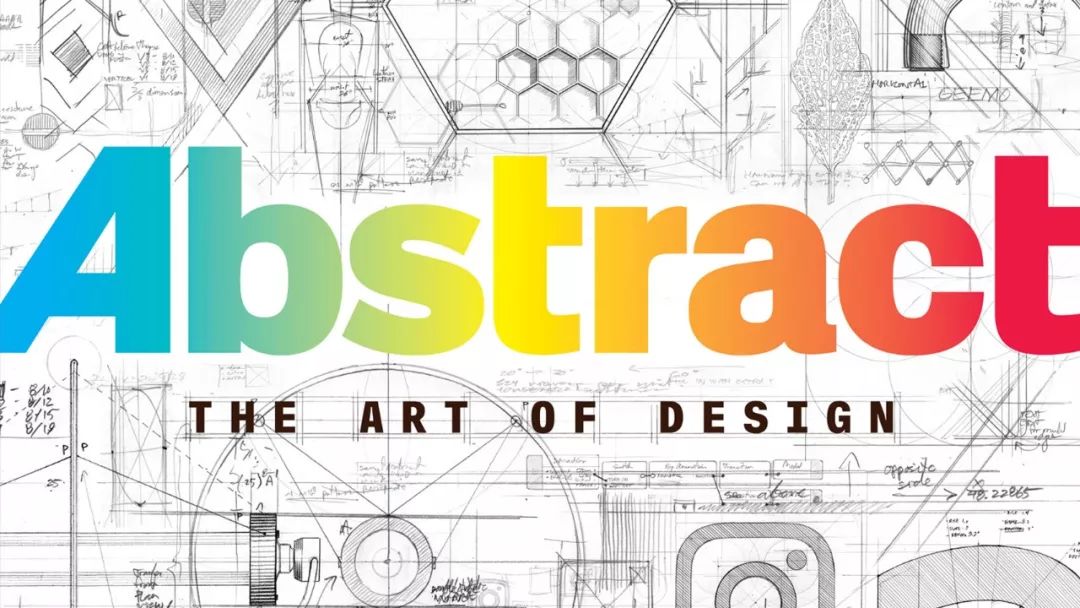
不愧是Netflix力作,一开播就引起巨大反响,目前豆瓣也已达到9.1分,预估有望超过第一季。
这一季由奥斯卡最佳纪录长片导演伊丽莎白·柴·瓦沙瑞莉执导,共探访了6位设计师。他们包括
玩材料的麻省理工美女博士
instagram前设计主管
漫威《黑豹》的服装设计师
脑洞大开的玩具设计师
《时尚芭莎》、《纽约时报》等原版杂志字体开创者
还有打造沉浸式体验鼻祖
与第一季不同的是,内容上更多的是介绍他们对设计的思考理解,从而让我们更好地理解什么是设计,以及创新设计真正的意义和价值。
「麻省理工的“疯子教授”」
Neri Oxman / 生物建筑
皮特的“绯闻女友”让很多人注意到了这位MIT的美女博士,但认识她的人,早已知道Neri Oxman 这个名字已经成为传奇。
建筑师、设计师、发明者三个身份集于一身,是一位名副其实的女学霸。作为世界建筑界的五位顶尖女设计师之一,连纽约现代博物馆、巴黎蓬皮杜艺术中心等全球顶级博物馆收藏着她的作品。
▲死亡面具
▲贵妃椅:采用44种不同的复合材料,由木质外壳和3D打印的细胞形状的表皮结合而成的躺椅
她创造并实践着一个新的词语“材料生态学(Material Ecology)”。试图通过“大自然启发设计”原则来增强建筑、自然和生物环境之间的关系。
希望在未来有更加新颖的技术发明,能广泛的应用于建筑、服装、产品等设计行业。
▲6500只蚕制造的蚕丝亭
融科技与设计为一体,理念前卫,造型独特是她作品的一惯风格。有精密生长的生物感,又有新材料带来的新鲜感,让人感觉空灵而神秘。
▲Rottlace
▲Aguahoja 项目
第一眼看到奈利的作品是惊呼美,当了解其中大致的科学原理,就会更崇拜她的创造力。因为这些非凡作品的背后,讨论的是改变人物未来的伟大决心和持之以恒的实践。
▲3D打印的生物可穿戴设备,其特点是可作为微生物的栖息地,在恶劣环境下能产生糖或生物燃料,维持使用者的生存
▲描绘的一种设计世界的新模式: 有机体世界
▲实现世界上第一个玻璃的3D打印
「Instagram 前设计负责人」
Ian Spalter / 产品设计
顶着一个爆炸头的潮酷伊恩,曾在Instagram、YouTube、Foursquare、R / GA 、Nike多家公司任职。在他看来,数字产品设计,不仅仅是用户体验设计,也关于整体产品策略,需要研究和考虑用户的使用需求。
2016年,Ins从相机logo换成现在的彩虹logo时,引起全球一片哗然,各种新闻媒体、社交媒体毫不留情的批评声此起彼伏。那是伊恩加入Instagram的第一个杰作。
▲目前拥有超10亿用户的社交应用软件Instagram
新logo采用扁平化、渐变色、非衬线体、动态化,外观更简洁直观,已经成为当下最流行的图标设计趋势。
片中伊恩从人机交互界面的历史谈起,界面作为人与机器之间交流的平台,在生活中如何被开发。
用户体验设计(UX)和交互界面设计(UI)的如何更加操作简化,方便用户的理解,通过更直观的感受,不需要经过学习直接就能使用。
设计需要针对人性以及市场深度需求,给出具体的解决方案才行,而不仅仅是关注“好不好看”。
「沉浸式体验鼻祖」
Olafur Eliasson / 艺术设计
奥拉维尔以雕塑和大型装置艺术而闻名,是目前最受青睐的十大国际艺术家之一,可以说世间万物都能被他玩转到一起,大到自然气象,小到各类金属。
自然、光、色彩和几何构成是他作品中不断出现的主题。使用人造装置来重现自然景观,把美感表达到极致,所以说他是沉浸式体验鼻祖。
他在巴黎的凡尔赛宫“挂瀑布”,在伦敦泰特博物馆“种太阳”,吸引数百万观众前去观赏奇观。
▲《天气项目》
▲小太阳计划:帮助全球11亿仍生活在无电网覆盖地区的人们,能够看到光亮
利用错觉触动观众的官能感知,参与者在其中失去空间感和视角,完全被强光所包含,被色彩、被几何的魅力所吸引。
他说得最多的话是把想法变成行动,这也是他的设计理念和工作模式,让观众去亲身感受、亲自参与,而不仅仅把作品停留在简单的看与思考的层面。
▲2007年伦敦蛇形画廊馆
▲丹麦城堡办公厅
「儿童玩具设计得最好的厨师」
Cas Holman / 玩具设计
卡斯是玩具设计界的多领域大神,但他是从厨师跳入家具制造,然后涉足生物多样性研究,参与幼儿教育,又攻读了3D设计,所以说不想做玩具的设计师不是个好厨子。
她第一个成功的玩具设计是Geemo,一个大型建筑套件玩具,于2006年在现代艺术博物馆的设计商店推出,这正式开启了卡斯的玩具职业生涯。
她设计的玩具通常由多种不同形状的建造单元组成,可以在户外或室内使用。孩子们可以自由拼接,组装出自己设计的物件和装置,为个人的想象留下更多空间,开发了孩子们的创造力。
她质疑传统玩具的形式,那种被符号化的风格在她看来并不是真正为孩子设计的产品。作为一名设计师,她要做能让儿童自由想象、探索想法和发明新事物的玩具。
「漫威电影《黑豹》的服装设计师」
Ruth Carter / 服装设计
她是一名美国电影服装设计师。2019年,漫威大片《黑豹》斩获奥斯卡最佳服装设计奖,露丝也成为首位获得奥斯卡服装设计奖的非洲裔美国妇女。
▲《黑豹》剧中服饰
在获奖之前,露丝几乎名不见经传,尽管她已经为40多部电影或电视剧设计服饰,也曾因为两部电影获得过提名。
对她而言,她觉得缝衣服这件事,就像是在讲故事。她给电影和戏剧的演员们设计服装,也是在为作品构建一个鲜活真实的世界。
露丝说她很喜欢观察街上的路人,人们用衣着记录生活,体现自身的价值观,想象他们经历过的故事。
抓住时代的精髓,结合不同文化场景的缩影,打造出适合他们的视觉身份。
「《滚石》《时尚芭莎》杂志字体开创者」
Jonathan Hoefler /  字体设计
生活在纽约的字体设计师乔纳森·霍夫勒,向观众们讲述了字体设计背后的故事。作为当今美国最知名的字体设计师之一。
曾为各个时期最有影响力的杂志设计过封面字体——《滚石》《体育画报》《时尚芭莎》《时尚先生》等,用于珠宝品牌 Tiffany & Co.品牌形象更新。
圈外人可能不熟悉他本人,但是他创建的Macintosh计算机字体和Gotham字体,随处可见,从苹果字体到奥巴马2018年总统大选海报设计。
▲霍夫勒创建的Gotham字体
▲奥巴马总统竞选海报
霍夫勒分享说,人类的在观看图案时会产生的视错觉现象 ,因此,为了让字体在视觉的呈现上更加和谐,设计师需要做一些调整,即使它暂时看起来不太合理。
字体作为承载人们信息交流的介质,必须满足功能需求,且具有可读性。从而构建出一套可被复制的标准,适用于不同场景的体系。
“Their work, is our world.”
他们的创作,造就了我们生活的世界。